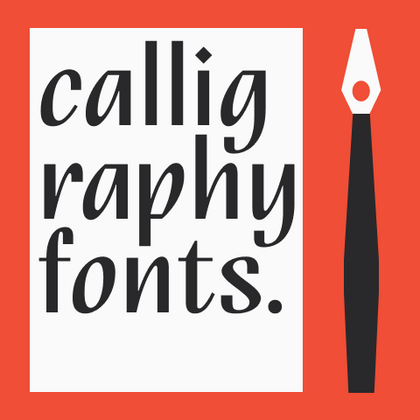
Каллиграфические Шрифты
Шрифты, основанные на каллиграфии, имитируют человеческий почерк. Поэтому если вы хотите придать дизайну ощущение рукотворности, каллиграфические шрифты — это то, к чему вам стоит присмотреться. Они могут быть прямыми или наклонными, мягкими или динамичными, и передавать разные настроения. В подборке представлены лучшие каллиграфические шрифты из коллекции студии.
TT Odellia — старостильная антиква с современным рисунком, вдохновлённая венецианскими шрифтами и классической музыкой.
TT Fellows — гуманистический гротеск с механистическими мотивами. Открытые формы, дружелюбно-нейтральный характер тонких весов и ещё более мягкий характер в жирных начертаниях.
TT Disruptors — дуктальный рукописный шрифт, созданный с помощью маркера. Его рисунок уникален: потёртости, неравномерная толщина штрихов и удлинённые выносные элементы придают ему живую, динамичную текстуру и ощущение рукотворности. Характер этого шрифта своенравный и эмоциональный, но при этом тёплый и душевный.
TT Ramillas — стильная и современная антиква. Включает уникальные декоративные начертания и буквицы с цветочным орнаментом.
TT Carvist — современный экспериментальный гротеск со сверхузкими пропорциями. Название гарнитуры отсылает к резьбе по камню: характерные черты этого шрифта — геометричность и брутальность.
TT Marxiana является проектом по реконструкции набора дореволюционных шрифтов, которые использовались в изготовлении и печати журнала «Нива» 1887 года выпуска, а именно на его антикве и италике, гротеске и эльзевире.
TT Knickerbockers Grotesk символизирует собой монументальность, выраженную в как в традиционной исторической застройке Нью-Йорка, так и в его небоскрёбах. Энергия, постоянное движение и круглосуточная жизнь Нью-Йорка — все это отразилось в нашем TT Knickerbockers Script.
TT Rounds Neue — мягкий и дружелюбный шрифт, который умеет быть разным. В тонких начертаниях он выглядит минималистично и нейтрально. В жирных же — «надувается» и округляется, приобретая инфантильные черты.
TT Fors — тот самый шрифт «для всего». Это стильный, лаконичный и функциональный геометрический гротеск с выверенными формами. Его можно использовать и в интерфейсах, и для создания акцентов.
TT Ramillas — стильная и современная антиква, которая украсит любой проект. Уникальные декоративные начертания и буквицы с цветочным орнаментом помогут создать неповторимый дизайн. Шрифт уже используется на 3000+ сайтах во всем мире, а также отмечен наградой Modern Cyrillic.
TT Berlinerins — это контрастная пара шрифтов, которая по сути является нашим трибьютом Берлину. Также, как и в самом городе переплетаются историчность и современность, так и в нашем шрифтовом семействе элегантный скрипт символизирует собой современный Берлин, а гротеск, выполненный в стиле плакатных wood-type шрифтов первой трети 20-го века, отвечает за историческую составляющую города.
TT Lovelies Script является очень живым и игривым шрифтом с небольшими нюансами непредсказуемости. В нем даже прописные буквы соединяются со строчными во всех случаях без разрывов. Каждая строчная буква имеет характерные росчерки, начинающие и заканчивающие слово.